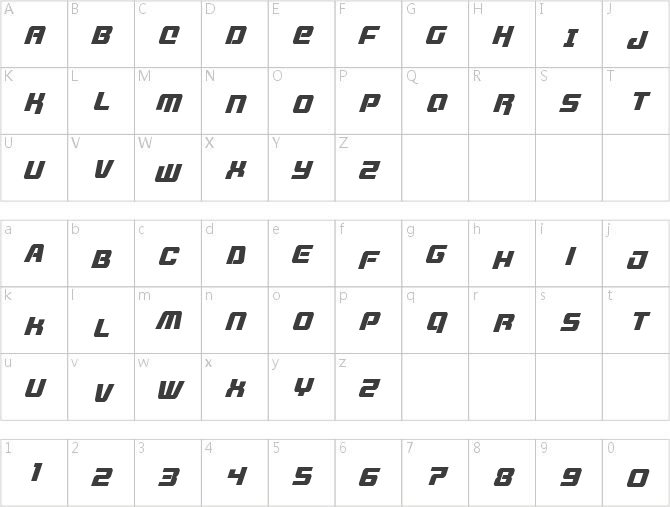
Livewired Condensed Italic
Livewired Condensed Italic介紹
Livewired Condensed Italic字體字庫是一款讓人賞心悅目、百看不厭的英文字體,適合各類廣告和產品包裝設計應用,字體大小0.02MB,格式為ttf字體,上傳用戶是……西央,作者/版權方為未知